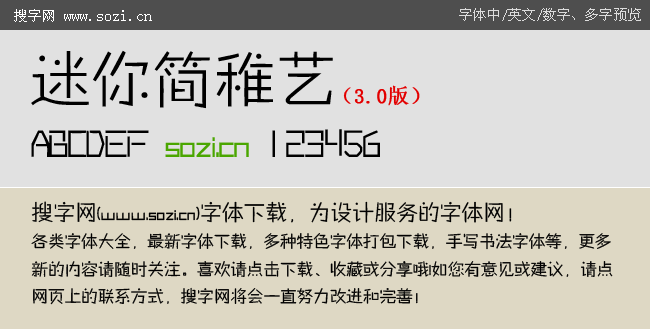
迷你簡(jiǎn)稚藝體
搜字網(wǎng)提供一款可愛(ài)卡通風(fēng)格的迷你簡(jiǎn)稚藝體字體,這款字體非常漂亮,帶有卡通風(fēng)味,活潑而不死板,是你pc必裝的字體之一。可以應(yīng)用于廣告設(shè)計(jì)、平面設(shè)計(jì)、印刷包裝、報(bào)紙雜志等行業(yè)。